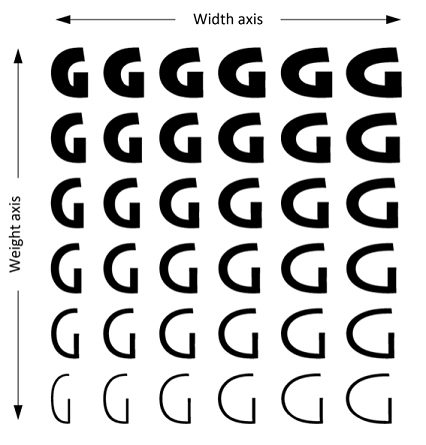
Tipi di carattere della variabile OpenType
Questo argomento descrive i tipi di carattere delle variabili OpenType, il supporto in DirectWrite e Direct2D e come usarli nell'app.
Che cosa sono i tipi di carattere delle variabili OpenType?
La versione 1.8 della specifica del formato del carattere OpenType ha introdotto una nuova estensione per il formato noto come OpenType Font Variations. I tipi di carattere che usano queste estensioni sono noti come tipi di carattere variabili OpenType. Un tipo di carattere variabile OpenType è un singolo tipo di carattere che può comportarsi come diversi tipi di carattere usando l'interpolazione continua tra diverse progettazioni, tutte definite all'interno del singolo tipo di carattere.
Un tipo di carattere variabile OpenType può definire una variazione continua della progettazione lungo uno o più assi indipendenti, ad esempio peso o larghezza:
Mostra un tipo di carattere variabile OpenType usando la lettera 'G' e mostra variazioni diverse lungo un asse di larghezza orizzontale e un asse di spessore verticale.
Uno sviluppatore di tipi di carattere determina un set di assi di variazione da utilizzare in un determinato tipo di carattere. Questi assi possono includere un set di assi noti (o "registrati") di variazione, ad esempio peso e larghezza, ma possono includere anche assi arbitrari e personalizzati di variazione definiti dallo sviluppatore di tipi di carattere.
Selezionando un set di assi di variazione per un tipo di carattere, lo sviluppatore di tipi di carattere definisce uno spazio astratto e ndimensionale della variante di progettazione per il tipo di carattere. I motori di testo possono specificare potenzialmente qualsiasi posizione, o "istanza", all'interno di tale spazio continuo per la disposizione e il rendering del testo.
Lo sviluppatore di tipi di carattere può anche selezionare e assegnare nomi a istanze particolari all'interno dello spazio di variazione della progettazione; questi vengono definiti "istanze denominate". Ad esempio, un tipo di carattere con variazione di spessore può supportare variazioni continue tra tratti molto leggeri e molto pesanti, mentre lo sviluppatore del tipo di carattere ha selezionato pesi particolari lungo tale continuum e assegna loro nomi, ad esempio "Light", "Regular" e "Semibold".
Il formato del tipo di carattere della variabile OpenType usa tabelle di dati presenti nei tipi di carattere OpenType tradizionali e alcune tabelle aggiuntive che descrivono come cambiano i valori di vari elementi di dati per istanze diverse. Il formato definisce un'istanza di variante come "istanza predefinita", che usa le tabelle tradizionali per ottenere i valori predefiniti. Tutte le altre istanze dipendono dai dati predefiniti e da altri dati differenziali. Ad esempio, una tabella "glyf" può avere una descrizione della curva di Bézier di una forma di glifo nominale, ovvero la forma utilizzata per l'istanza predefinita, mentre una tabella "gvar" descrive come i punti di controllo di Bezier per il glifo vengono modificati per altre istanze. Analogamente, altri valori dei tipi di carattere possono avere un valore nominale più dati differenziali che descrivono come tali valori cambiano per istanze diverse; ad esempio, altezza x e altre metriche a livello di carattere o posizioni di ancoraggio del contrassegno specifiche del glifo e regolazioni della crenatura.
Poiché i tipi di carattere variabile possono supportare un set arbitrario di assi di varianti, richiedono un modello estendibile di famiglie di caratteri che riflettono più direttamente il modo in cui i progettisti di tipi di carattere creano famiglie di tipi di carattere: una famiglia di caratteri è definita da un nome di famiglia e determinate caratteristiche di progettazione costanti, con un numero arbitrario (determinato dallo sviluppatore di tipi di carattere) di modi in cui la progettazione può variare. È possibile creare una famiglia di caratteri con varianti per il peso, ma è possibile creare una famiglia di caratteri diversa con varianti per x-height, serif-size, "funkiness" o qualsiasi cosa lo sviluppatore del tipo di carattere desideri. In questo modello, una selezione del tipo di carattere è descritta meglio usando il nome generale o "preferito" o "tipografico", il nome della famiglia più un set di coppie chiave-valore, ognuna che rappresenta un tipo di variazione e un valore specifico, con i tipi di variazione in generale essendo un set estendibile. Questa nozione generale di una famiglia di caratteri può essere applicata ai tipi di carattere tradizionali, non variabili e ai tipi di carattere variabili. Ad esempio, in questo modello generale di famiglia tipografica, una famiglia "Selawik VF" potrebbe avere variazioni per peso, dimensioni ottiche e design serif, con istanze come "Sans banner semilight".
Alcune implementazioni software esistenti, tuttavia, incluse le API DirectWrite esistenti, possono essere progettate presupponendo un modello più limitato di famiglie di caratteri. Ad esempio, alcune applicazioni possono presupporre che una famiglia di caratteri possa avere al massimo varianti Regular, Bold, Italic e Bold Italic. Le interfacce IDWriteFontCollection e IDWriteFontFamily presuppongono un modello di famiglia weight/stretch/style ("WSS"), consentendo di specificare varianti all'interno di una famiglia usando le enumerazioni DWRITE_FONT_WEIGHT, DWRITE_FONT_STRETCH o DWRITE_FONT_STYLE come parametri. Prendendo l'esempio precedente, le dimensioni ottiche e gli assi serif non vengono considerati assi interni della famiglia di variazioni nel modello WSS.
Il supporto completo per i tipi di carattere delle variabili richiede api che consentono di specificare un membro della famiglia con potenzialmente diversi parametri, come determinato dal tipo di carattere. Tuttavia, le progettazioni API esistenti possono essere in grado di fornire supporto parziale per i tipi di carattere variabili proiettando le istanze denominate definite in un tipo di carattere variabile nei modelli della famiglia di caratteri più limitati. Nell'esempio precedente, "Selawik VF Semilight Banner Sans" potrebbe essere proiettato nel modello WSS come famiglia "Selawik VF Banner Sans" con "Semilight" come variante di peso.
Per un altro esempio, si consideri una famiglia di caratteri tipografici come Sitka, con varianti di peso e dimensioni ottiche. Le varianti denominate all'interno della famiglia includono Sitka Text Regular e Sitka Banner Bold (più molti altri). Il nome della famiglia tipografica è "Sitka", mentre i nomi dei visi per queste varianti nel modello di famiglia tipografica sarebbero "Text Regular" e "Banner Bold". I modelli di famiglia di quattro membri e WSS non consentono varianti di dimensioni ottiche all'interno di una famiglia, quindi le distinzioni delle dimensioni ottiche devono essere trattate come distinzioni a livello di famiglia. Nella tabella seguente viene illustrato come una selezione di tipi di carattere della famiglia tipografica Sitka verrebbe trattata nel modello di famiglia WSS:
Modello di famiglia tipografico
Modello di famiglia WSS
Famiglia
Faccia
Famiglia
Faccia
Sitka
Testo normale
Testo Sitka
Analogamente, se un'app usa IDWriteFontFallbackBuilder per creare dati di fallback dei tipi di carattere personalizzati, le famiglie vengono specificate per i mapping di intervalli di caratteri usando nomi di famiglia compatibili con WSS. Il fallback dei tipi di carattere all'interno di DirectWrite si basa sulle famiglie con DirectWrite che seleziona una variante all'interno di una famiglia di fallback che rappresenta una corrispondenza più vicina per la variante della famiglia iniziale. Per le varianti che prevedono dimensioni diverse da peso, estensione e stile, DirectWrite attualmente non sarà in grado di selezionare tali varianti all'interno di una famiglia di fallback a meno che non siano stati creati dati di fallback personalizzati specificamente per fornire mapping di fallback per le famiglie con attributi non WSS specifici, ad esempio varianti di dimensioni ottiche "Caption".